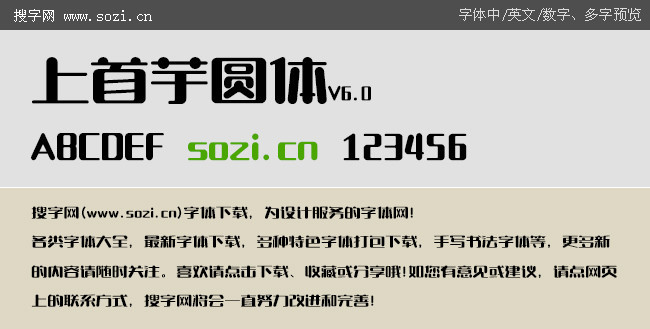
上首芋圓體V6.0
搜字網(wǎng)給大家提供一款上首芋圓體V6.0中文字體下載,上首芋圓體字體筆畫圓潤(rùn),Q彈可愛(ài),橫平豎直,憨態(tài)可掬,筆畫端點(diǎn)處整體導(dǎo)圓處理(本版本為升級(jí)版)。適用于搭配標(biāo)志、廣告標(biāo)語(yǔ)、商業(yè)廣告等廣告設(shè)計(jì)。